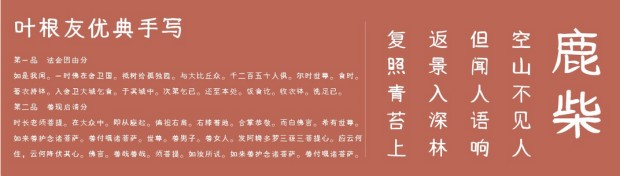
葉根友優(yōu)典手寫
葉根友優(yōu)典手寫體葉根友最新的一款字體,這款字體字形非常漂亮,并且每一筆每一畫都有獨特的味道哦,有喜歡的就來綠色資源網(wǎng)下載吧!
葉根友優(yōu)典手寫體介紹
葉根友優(yōu)典手寫體是一款優(yōu)雅而又不失大氣的手寫體,筆畫橫豎間都有一種剛毅而自在的筆尖感。